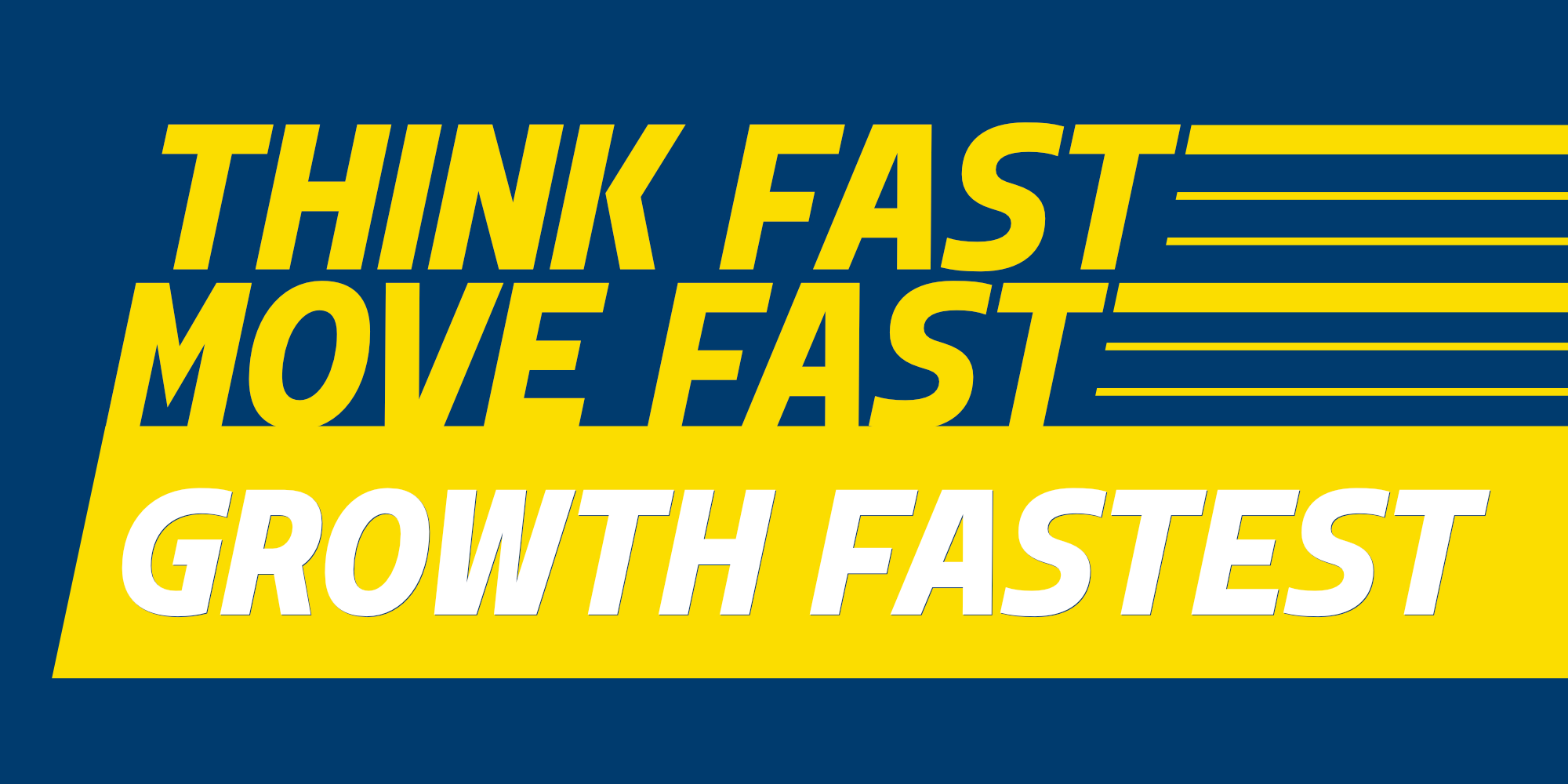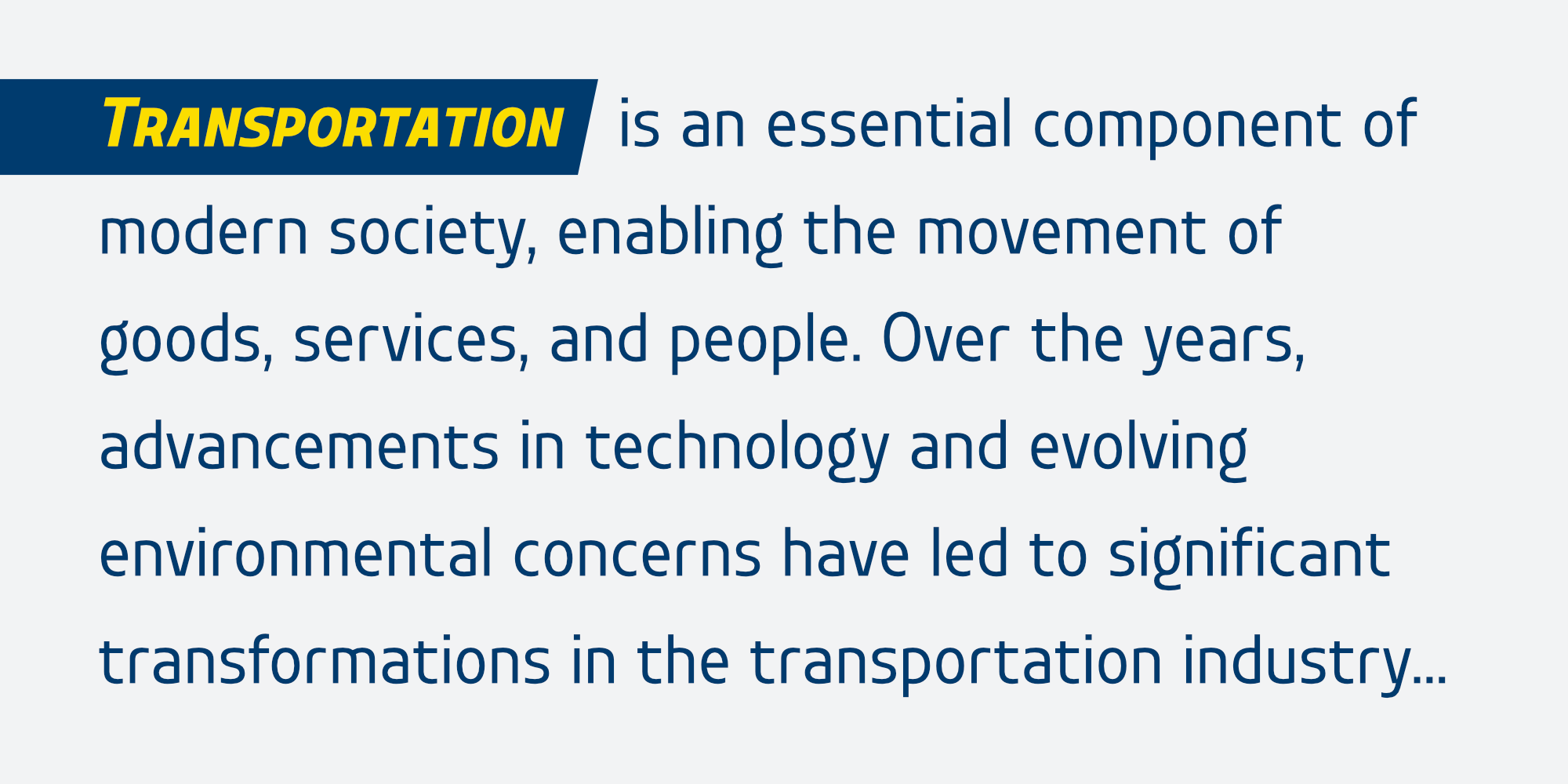
ขนส่ง | Khonsong
ชื่อฟอนต์ : ขนส่ง | Khonsong
ขอแนะนำฟอนต์ Khonsong ฟอนต์แบบ semi-condensed sans serif ซึ่งผสมผสานความทันสมัยและอนาคตเข้าด้วยกันอย่างกลมกลืน ด้วยรูปลักษณ์ที่โฉบเฉี่ยวและร่วมสมัย ความกว้างแบบ semi-condensed ทำให้มีความสมดุลที่สมบูรณ์แบบระหว่างการประหยัดพื้นที่และความสามารถในการอ่าน ทำให้เป็นตัวเลือกที่เหมาะสำหรับการใช้งานที่หลากหลาย ตั้งแต่สื่อออนไลน์ไปจนถึงสื่อสิ่งพิมพ์
Introducing "Khonsong," a semi-condensed sans serif font that embodies a harmonious blend of modernity and futurism. With its sleek and contemporary appearance, Its semi-condensed proportions strike a perfect balance between space-saving efficiency and legibility, making it an ideal choice for various applications,  from online media to print media.